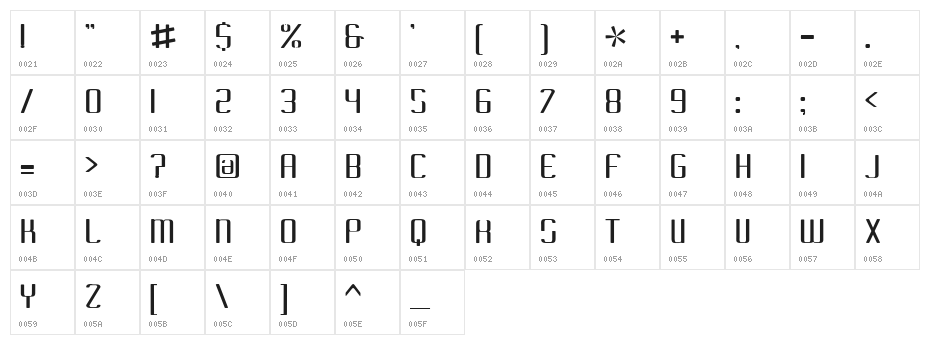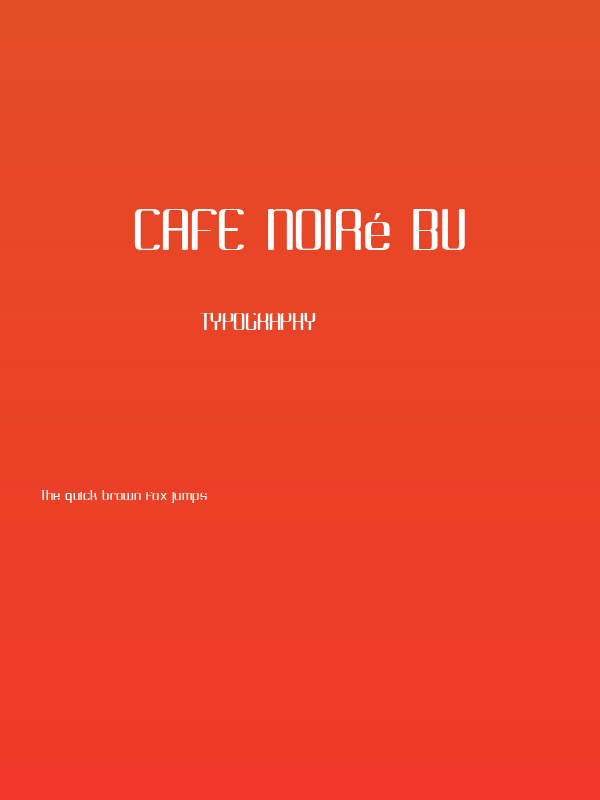
Cafe Noiré BV Font
| Caso d'uso | Headlines, Logos, Digital Media |
| Progetti proposti | Ideal for branding, advertising, and digital media projects that require a modern and clean aesthetic. |